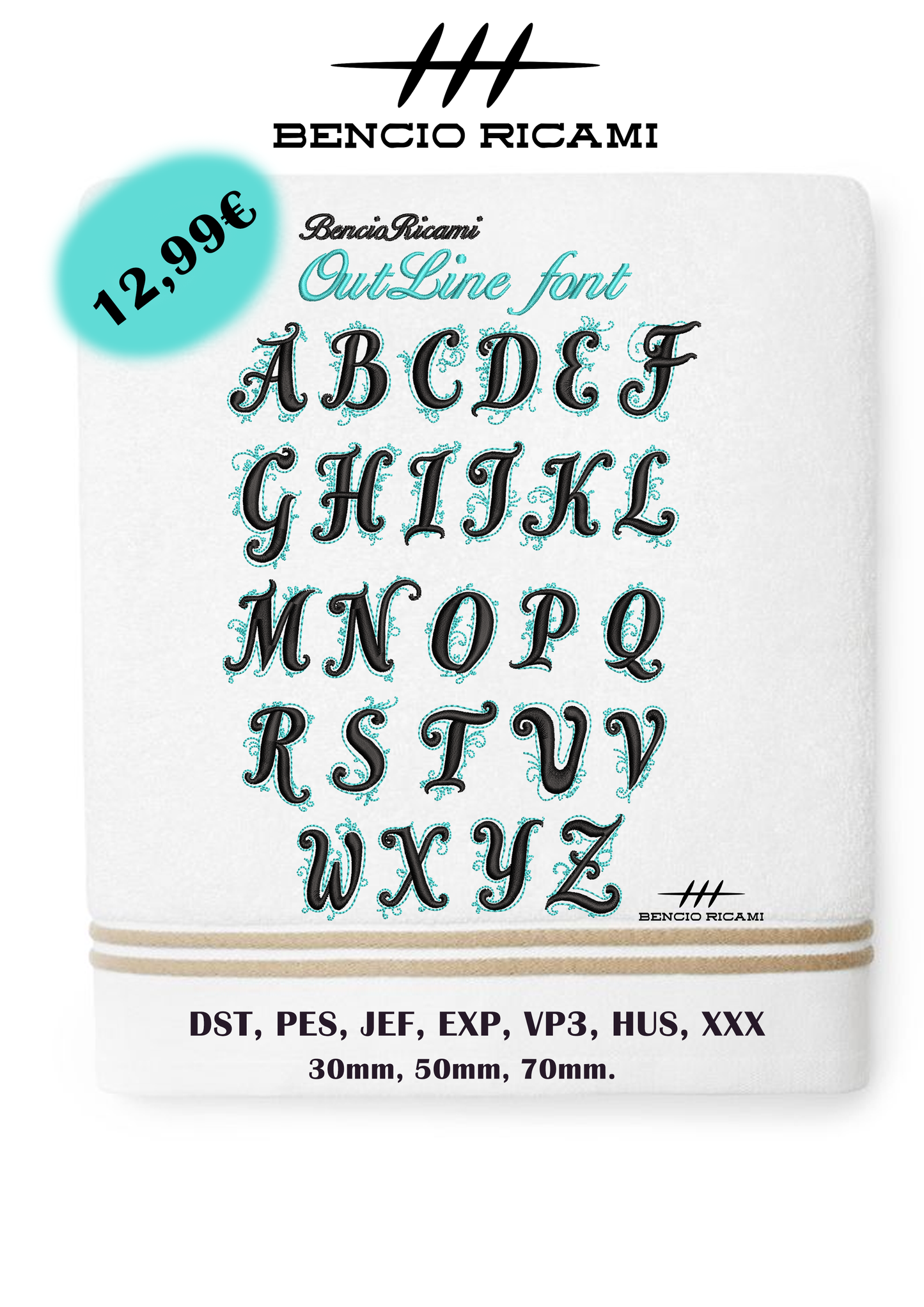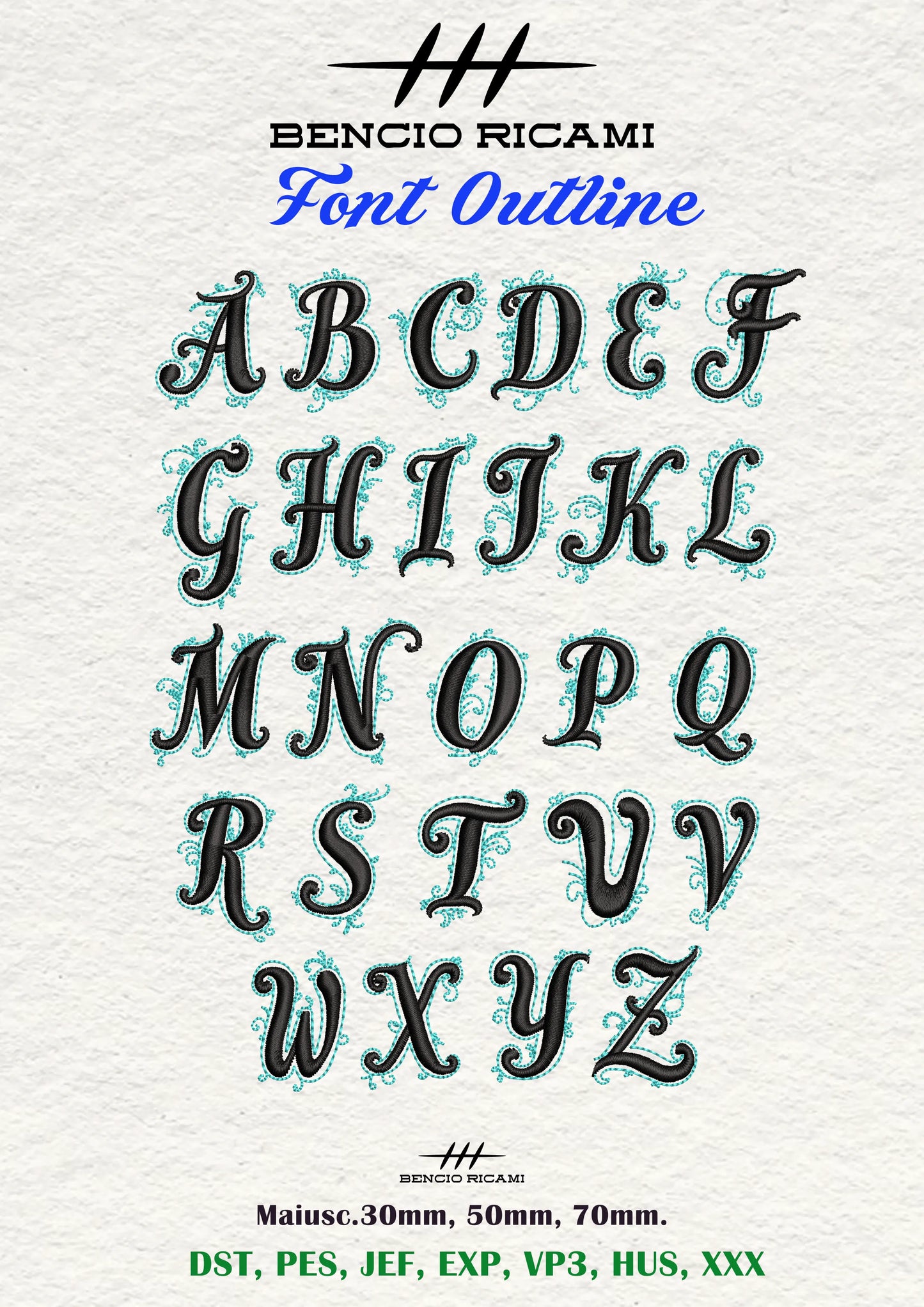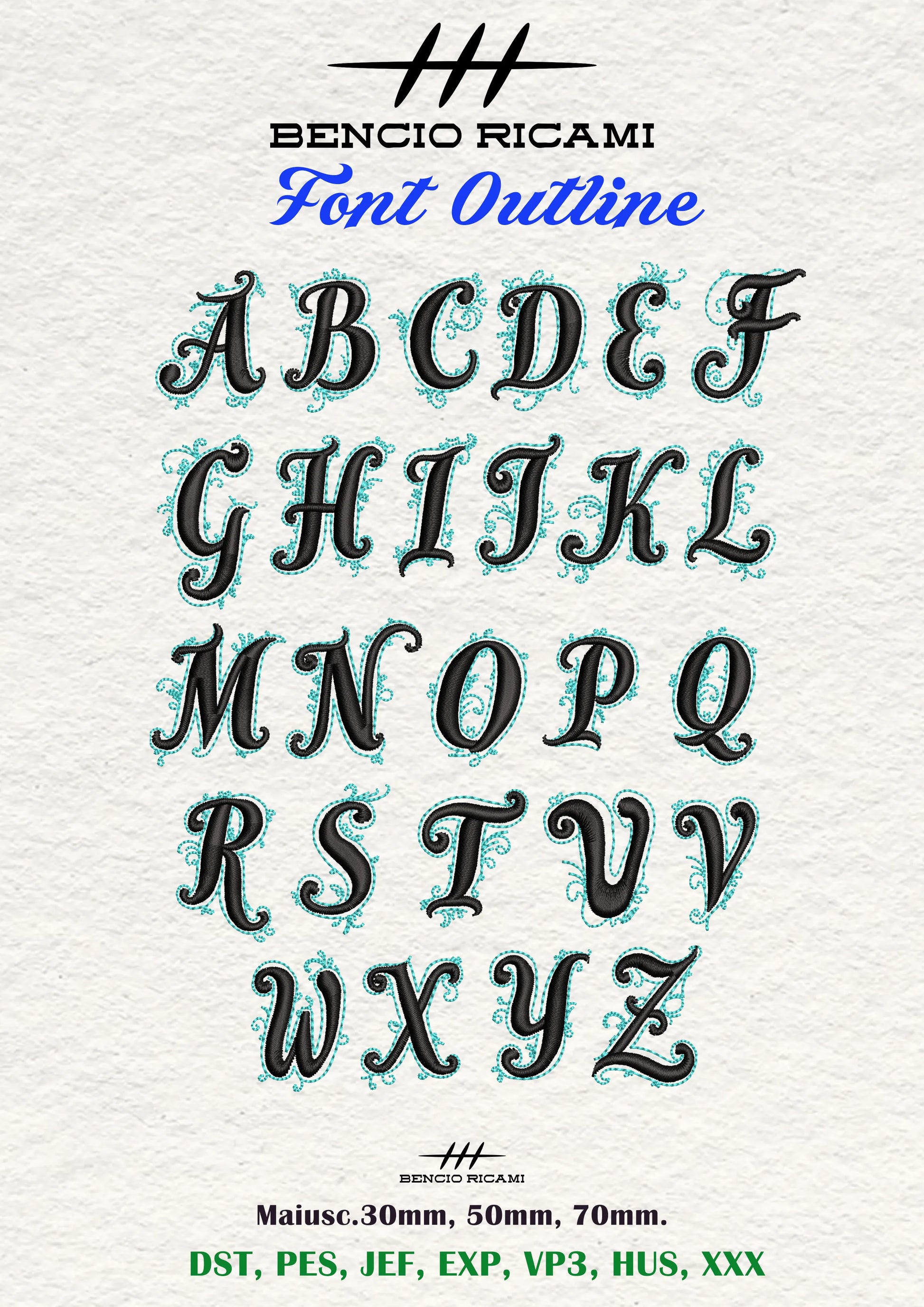
Font da Ricamo "Outline"
Aggiungi un tocco elegante e professionale ai tuoi ricami con Outline, un font raffinato e versatile, perfetto per personalizzazioni su asciugamani, accappatoi, bavaglini, fiocchi nascita, abbigliamento, accessori e molto altro.
Il carattere è stato digitalizzato con attenzione ai dettagli per garantire un ricamo pulito e ben definito su diversi tipi di tessuto.
✅ Alfabeto completo maiuscolo